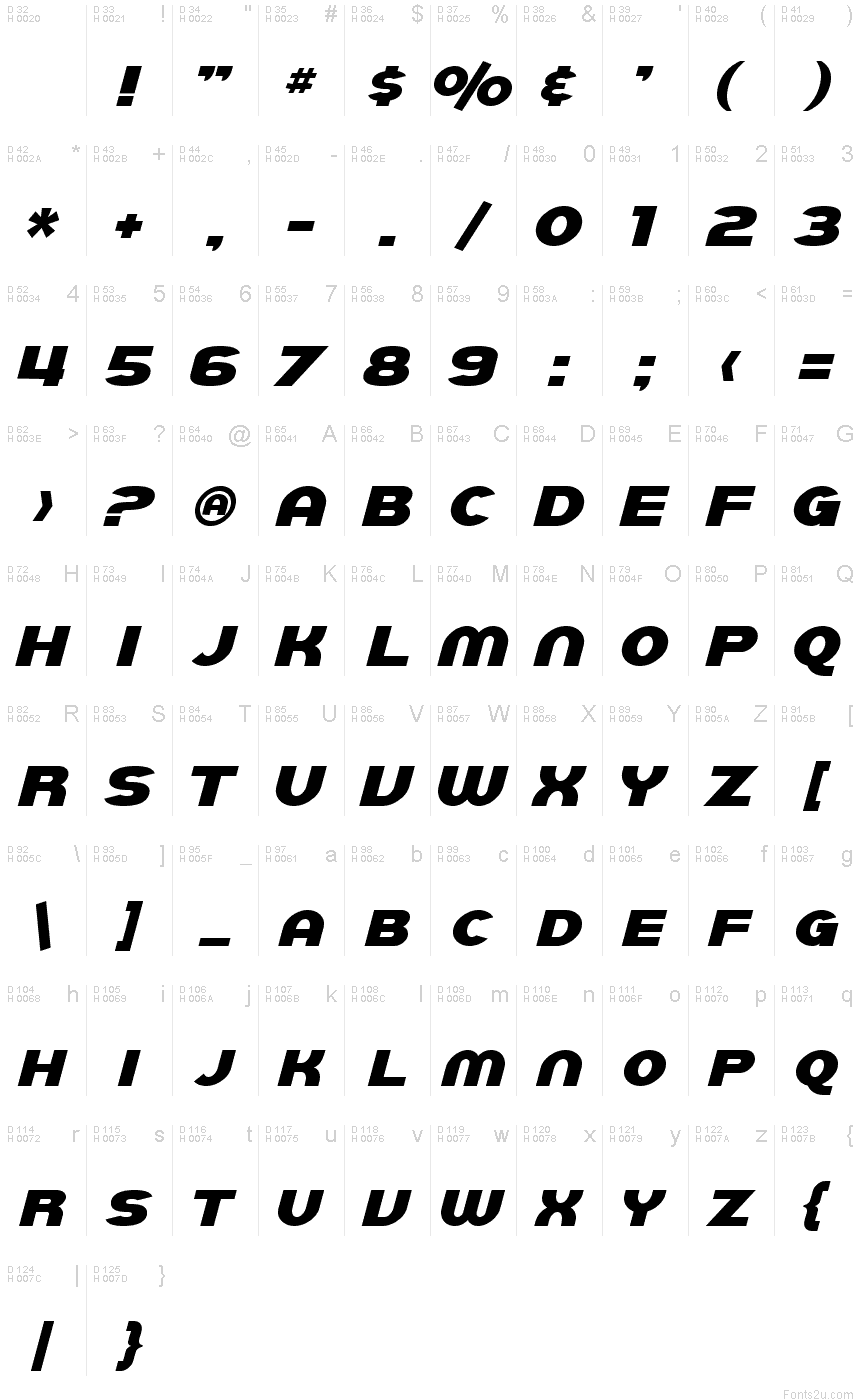
SF Juggernaut Italic od ShyFoundry to darmowy, futurystyczny krój typu display o drapieżnym, pochylonym charakterze. Wielkie litery sprawiają wrażenie wyciosanych jednym szybkim, ciężkim pociągnięciem – tępe cięcia, szerokie łuki i niskie, wyciągnięte łączenia nadają literom muskularną, technologiczną aurę późnych lat 2000.
Naturalnie sprawdza się w logotypach gier, brandingu sportowym, na plakatach, okładkach albumów i w motion designie, gdzie ten darmowy font może podkreślić dynamikę, nie stając się przy tym zbyt wygładzonym. Użyj go do krótkich nagłówków, warstwowych inicjałów lub monogramów, jeśli chcesz, aby litery sprawiały wrażenie dociśniętych ruchem, zachowując jednocześnie solidną, blokową formę.
SF Juggernaut
ShyFoundry
Derek Vogelpohl